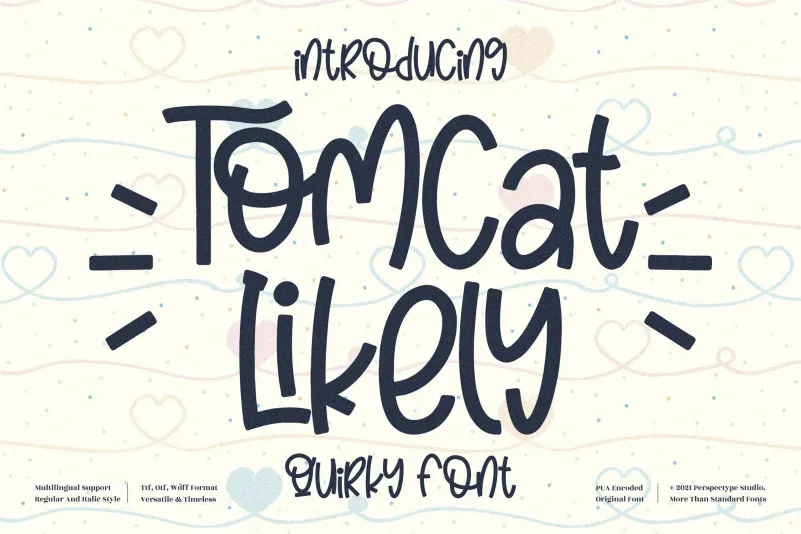
Esta é uma fonte escrita à mão que transmite frescura e charme com suavidade y cool. É ideal para qualquer projeto que busque uma pitada diferente, independente do tópico. Esta fonte pode ser um incrível ativo para sua biblioteca de fontes, pois tem o potencial de dar um salto a todos os seus trabalhos. Para designers e amantes dos recursos gráficos, esta é uma descoberta que não pode passar despercebida. A perspectype trouxe ao mundo algo único e versátil, com este ‘Tomcat Likely Font’ da categoria Script Fonts. Seja para criar um design criativo ou decorar seu próximo trabalho, a fonte de mão livre desta fonte vai trazer o toque especial que sua criação merece. Sua presença na sua biblioteca de recursos não só valorizará seus projetos, como também poderá servir como uma paleta inesperada para qualquer projeto que você estiver criando.